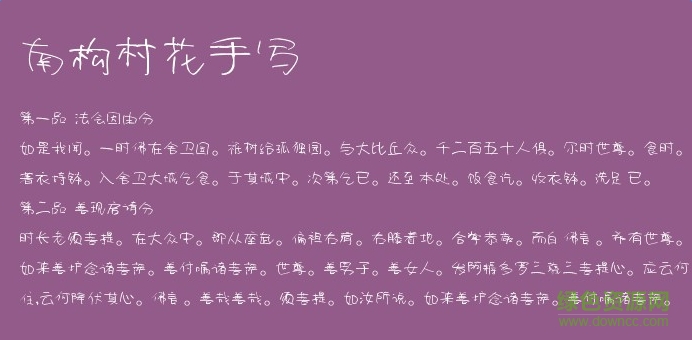
南構(gòu)村花手寫字體是一款非常獨特的手寫字體,該字體爽朗大方,可用來制作個性海報和各種卡通圖畫文案,喜歡的朋友歡迎在綠色資源網(wǎng)下載!
該字體原型是由成都才女、美食達人劉婕書寫的字體,風(fēng)格簡潔大方,流淌著一種對生活、工作美的追求的另一面,因為網(wǎng)名是村花、周圍的朋友們也叫她為村花,故取名南構(gòu)村花手寫,是不是真的像村花那么美呢?